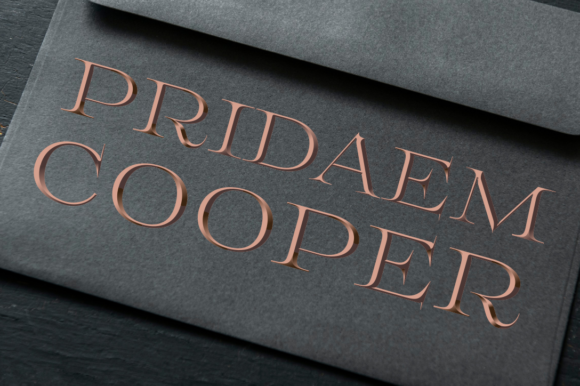
Pridaem Cooper
Pridaem Cooper – A Fonte Colorida que Transformará Seus Projetos
Se você está em busca de uma tipografia que una estilo e versatilidade, Pridaem Cooper é a escolha certa. Essa fonte colorida (OpenType‑SVG) destaca‑se pela qualidade visual e pela ampla gama de aplicações, tornando‑se um verdadeiro must‑have para designers, empreendedores e criativos.
- Design moderno e vibrante: cada glifo traz cores integradas que dão vida instantânea a logotipos, convites de casamento e cabeçalhos.
- Versatilidade de uso: perfeita para camisetas, papel timbrado, sinalização, etiquetas, newsletters, pôsteres, crachás e muito mais.
Por Que Pridaem Cooper Vale o Investimento?
Com a tendência crescente de designs vibrantes e personalizados, ter uma fonte que já traz cor embutida elimina etapas de edição e acelera o fluxo de trabalho. Além disso, a qualidade SVG garante que seu trabalho fique impecável tanto em telas quanto em materiais impressos.